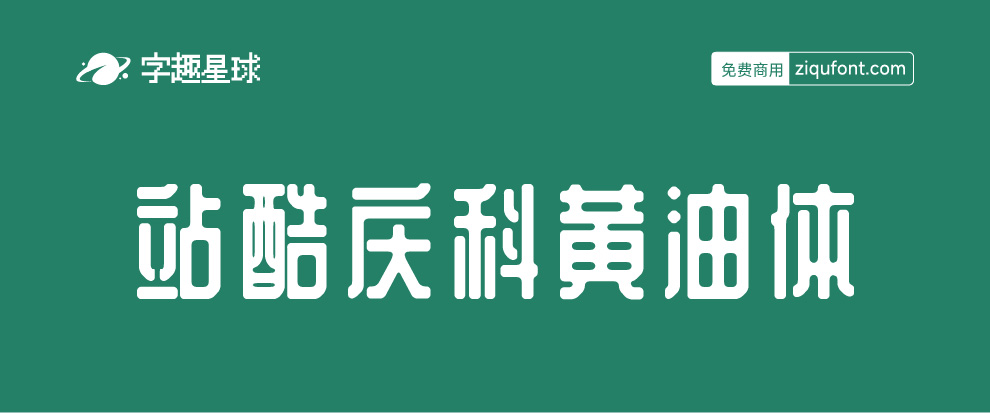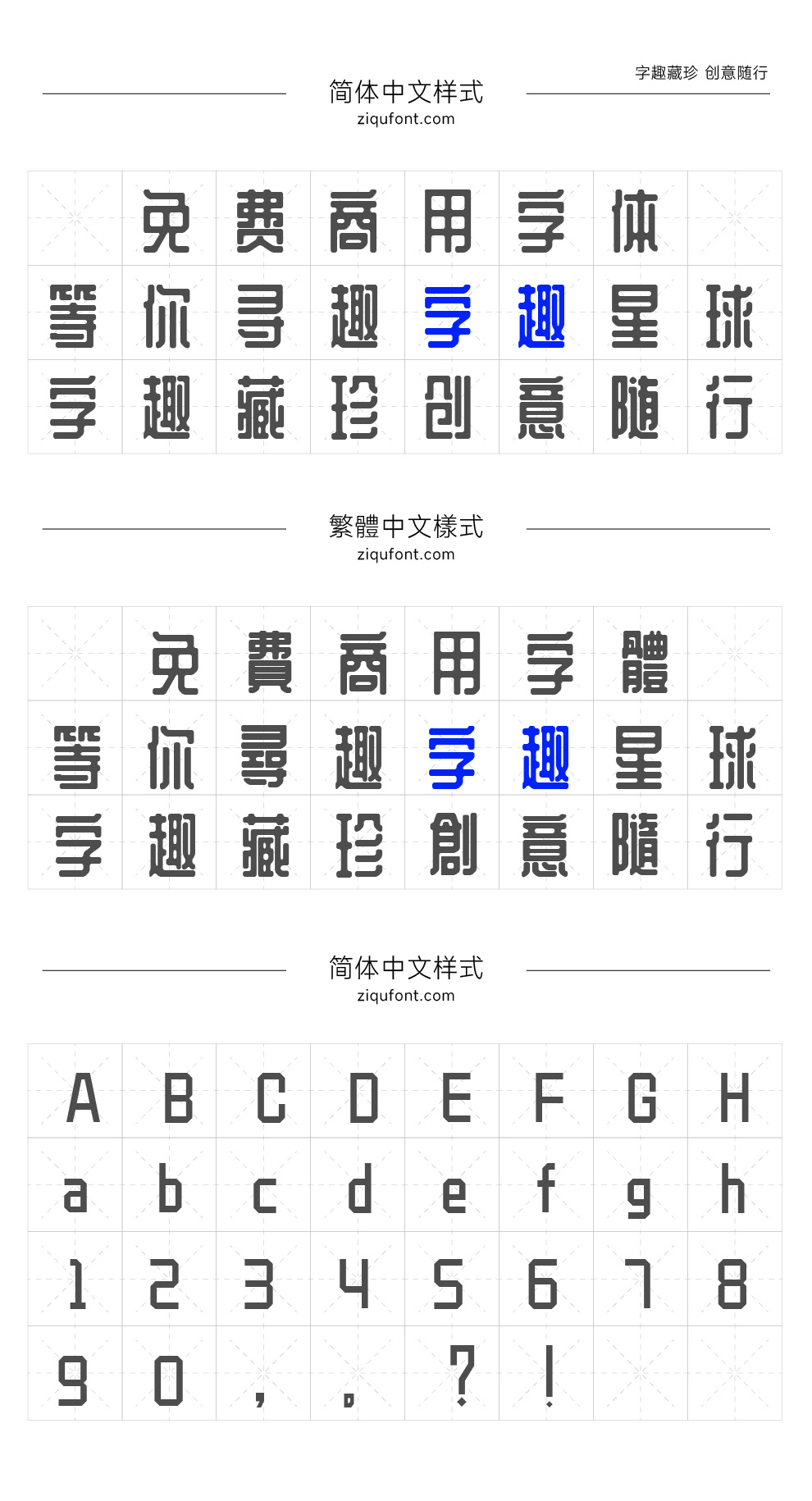
站酷庆科黄油体
站酷庆科黄油体是一款字型创新、线条圆润的字体。笔划的每一个直角,都被处理成了半径为4pt的圆角。在设计中需遵循笔划简化但不省略,笔划角度尽量为垂直角度。字体部首的右下角均为45°缺角,提高了字体视觉中心,并有效的解决了一些字体因笔划交叉,字体阅读困难的毛病。
郑庆科黄油体字体是一款用于创意设计方面的字体,该字体紧凑,识别性强,端正大方,整体风格出色。 它的英文字体和数字的风格跟中文汉字的样式其实是两种不尽相同的风格,郑庆科黄油体的英文字母与数字采用了折叠式设计思路,让人看起来就像是长条的纸张折叠出来的效果!
郑庆科黄油体这款中文字体整体偏可爱的风格,特别适合当店招、banner、标志、等领域,设计效果十分出色!